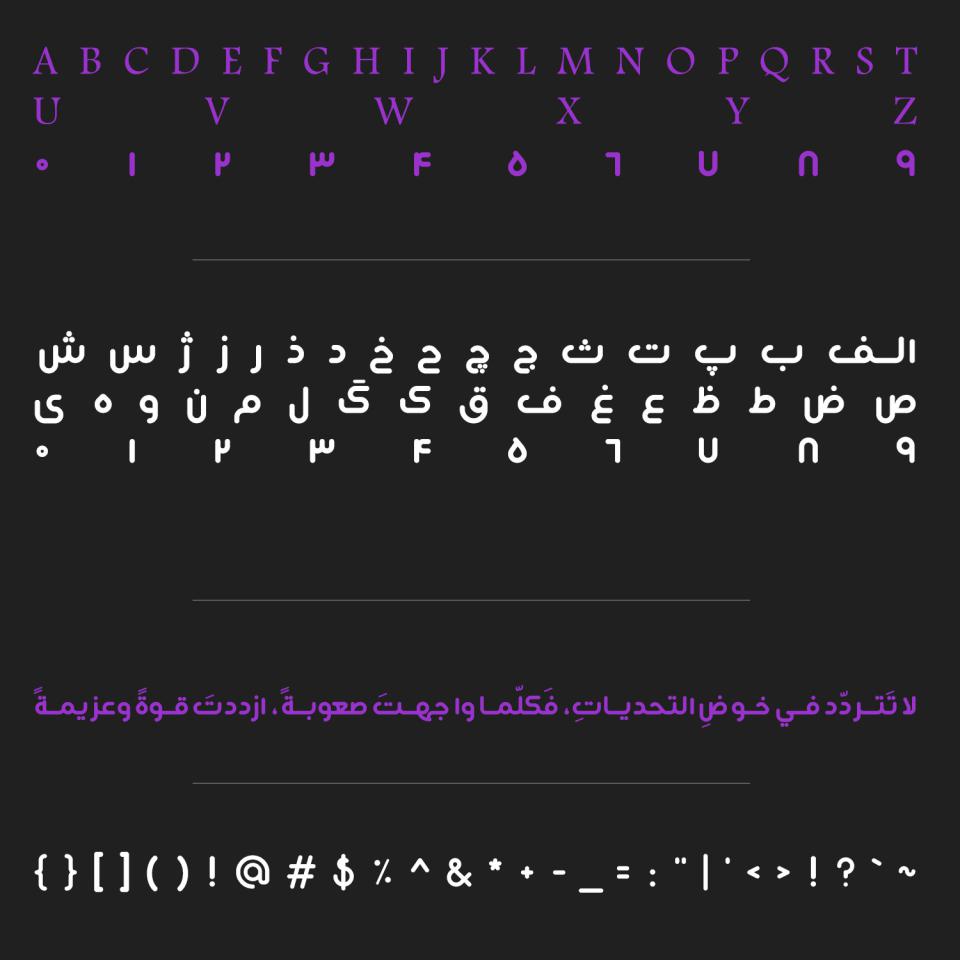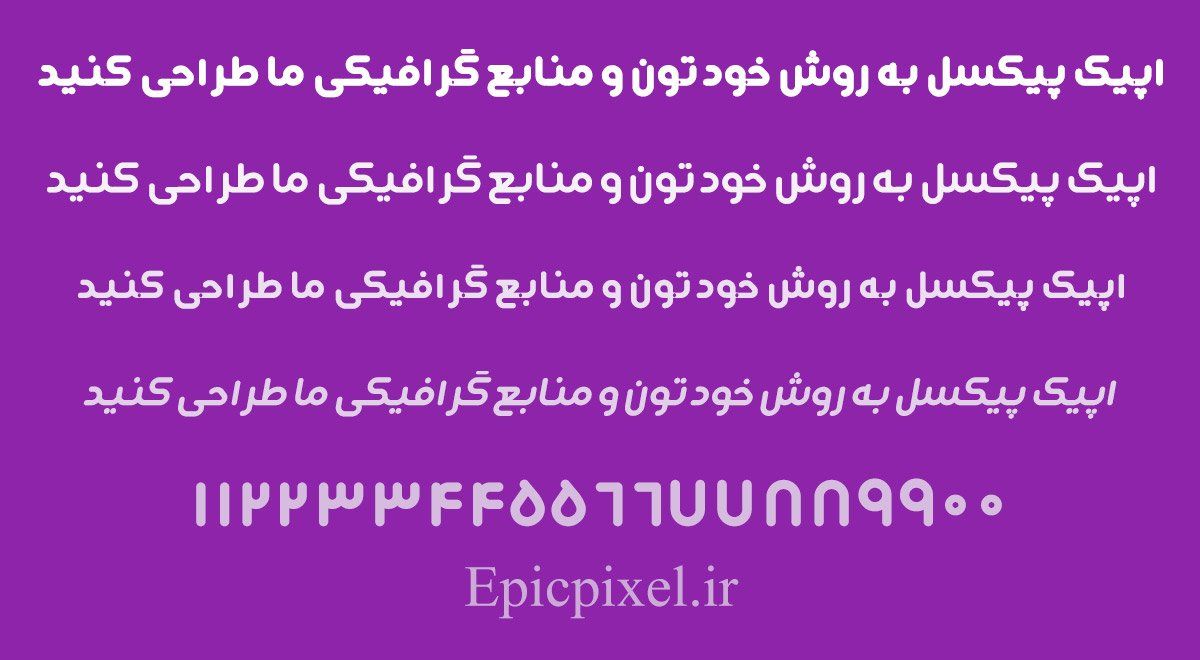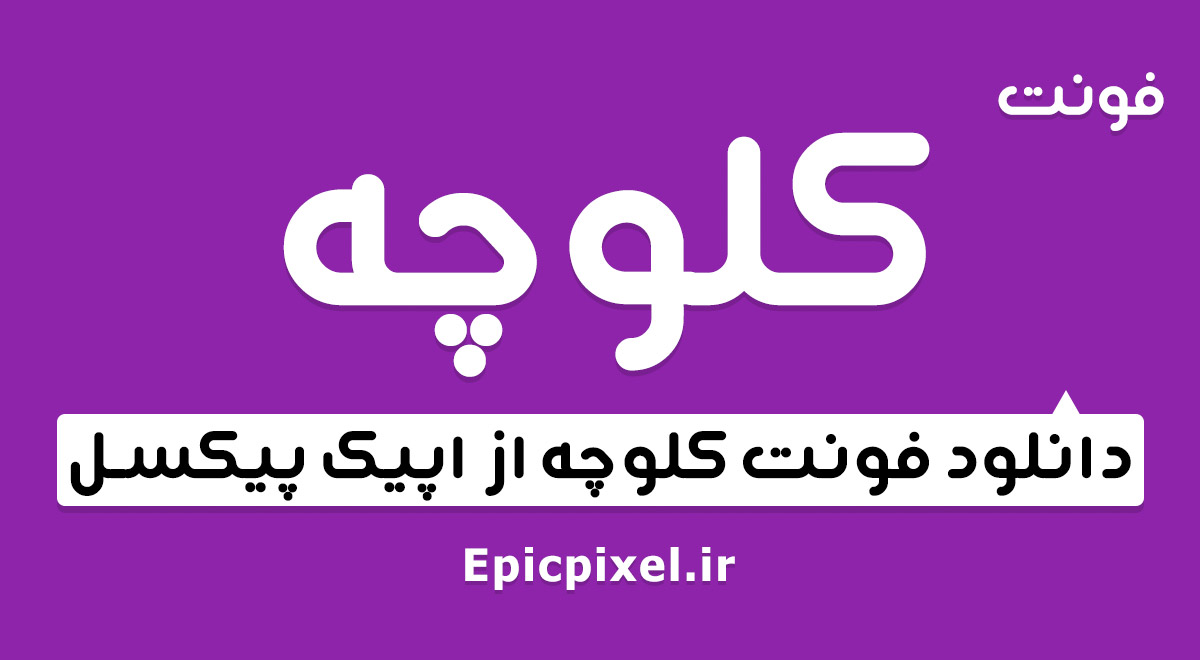
2 فونت کلوچه فارسی Koloche
فونت کلوچه فارسی، با ظاهر فانتزی و دوست داشتنی اش، انتخابی ایده آل برای پروژه هایی است که نیاز به حسی صمیمانه و کودکانه دارند. این فونت، با خطوط نرم و گرد خود، گرمی و صمیمیتی خاص به متن می بخشد و می تواند در طراحی هایی مانند کارت پستال های تبریک، بسته بندی محصولات کودکان، عناوین جذاب در وب سایت ها و شبکه های اجتماعی، و حتی طراحی های چاپی مانند پوسترها و بروشورها، جلوه ای ویژه ایجاد کند.
یکی از ویژگی های برجسته فونت کلوچه، خوانایی بالای آن در اندازه های مختلف است. این بدان معناست که چه در متن های کوتاه و چه در پاراگراف های طولانی، چشم مخاطب به راحتی می تواند حروف را دنبال کند و از خواندن لذت ببرد. این ویژگی، فونت کلوچه را به گزینه ای مناسب برای استفاده در محیط های دیجیتال و چاپی تبدیل کرده است.
با وجود ظاهر فانتزی، فونت کلوچه از انسجام و هماهنگی خوبی در طراحی حروف برخوردار است. این هماهنگی باعث می شود متن ها یکدست و زیبا به نظر برسند و از پراکندگی و ناهماهنگی بصری جلوگیری شود. این ویژگی در طراحی لوگو و عناوین کوتاه بسیار اهمیت دارد.
البته، باید به این نکته نیز اشاره کرد که به دلیل سبک فانتزی و خاص این فونت، ممکن است برای متن های رسمی و اداری مناسب نباشد. اما در عوض، در پروژه های خلاقانه و غیررسمی، می تواند عنصری جذاب و چشمگیر باشد. رایگان بودن این فونت هم مزیتی دیگر است که دسترسی آسان و بدون هزینه را برای همه فراهم می کند. پس اگر به دنبال فونتی هستید که به طراحی هایتان روح ببخشد و حسی دلنشین منتقل کند، فونت کلوچه فارسی انتخابی عالی خواهد بود.